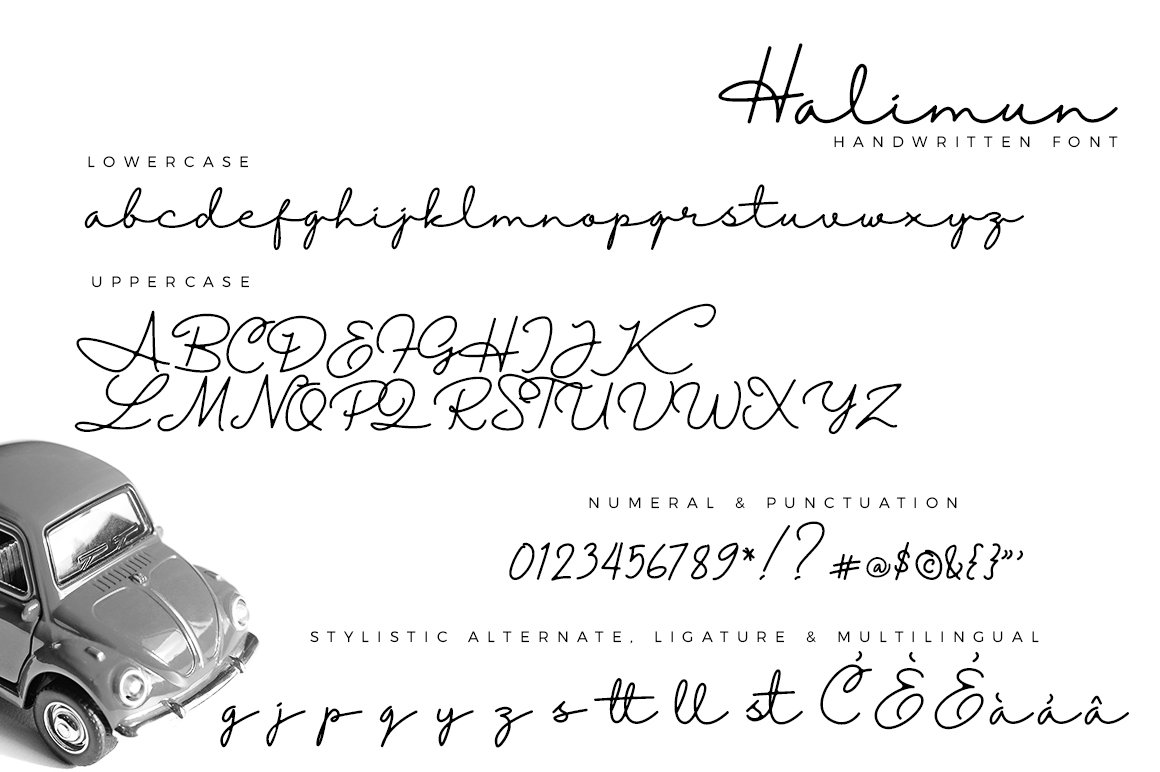
Halimun Font
Description de Halimun Font
Halimun Font, un nouveau script moderne et frais avec un style manuscrit et script, donne à cette police un aspect élégant, naturel, élégant et parfait pour tous les projets impressionnants qui nécessitent un goût d’écriture manuscrite.